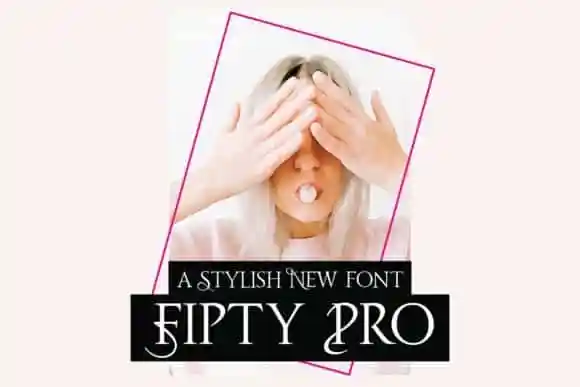
Fipty Pro Serif Font – Fonte Grátis
Fipty Pro Serif Font
Descubra Fipty Pro Serif Font, uma fonte serif que revive as estéticas vintage dos anúncios antigos para criar textos atraentes e memoráveis. Esta fonte inova nas versões modernas de anúncios tradicionais, mantendo seu charme clássico com um toque de sobriedade atual. Fipty é uma tipografia elegante e moderna que combina características distintivas, linhas suaves e alternativas memoráveis para criar textos que se destacam em qualquer projeto. Ideal para designers gráficos que valorizam a sofisticação e o estilo dos anúncios antigos, Fipty Pro é uma homenagem aos belíssimos desenhos de caligrafia. A fonte traz um toque romântico às suas criações, tornando-a perfeita para aplicações que precisam ser memoráveis e impactantes. Em uma era onde a simplicidade vira moda, Fipty Pro oferece ao designer gráfico mais do que apenas letras bem feitas. Com sua paleta de alternativas únicas, você pode personalizar seu projeto como nunca antes. Este é o momento perfeito para reviver os tempos dos anúncios impressos e reinventar-os em uma fonte moderna e sofisticada. Experimente Fipty Pro Serif Font hoje e deixe que sua criação seja um hit entre seus clientes.